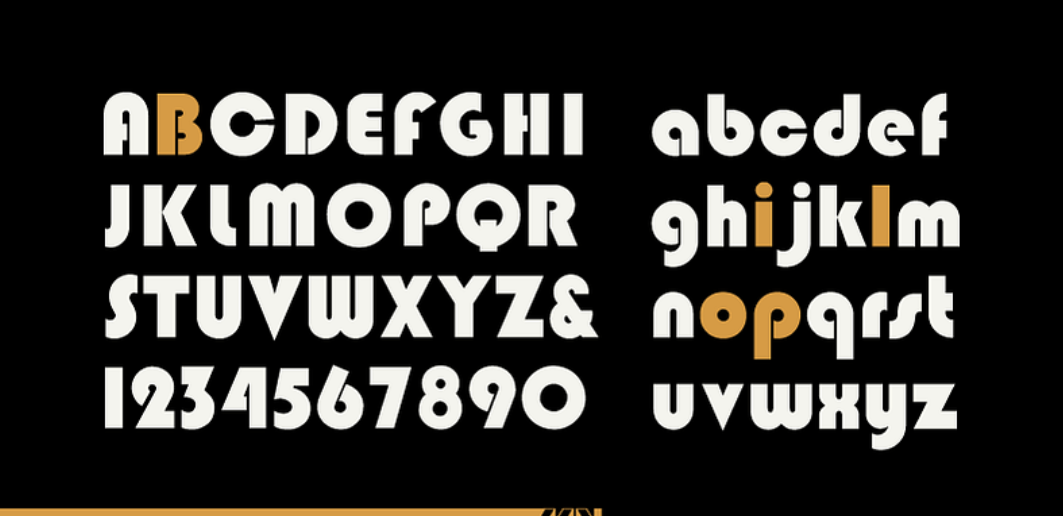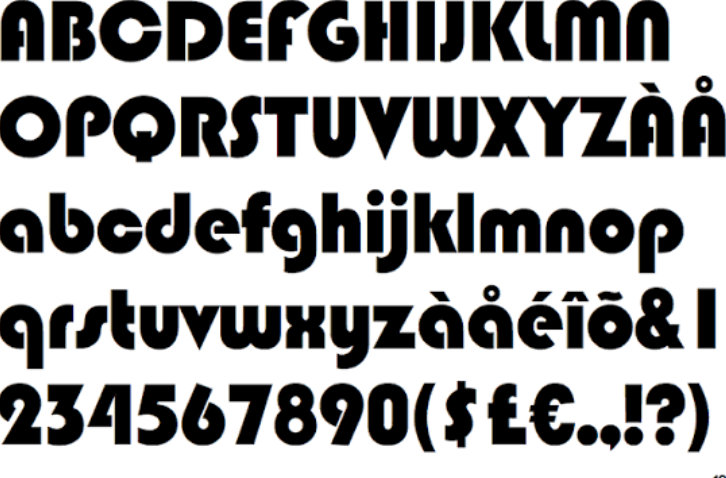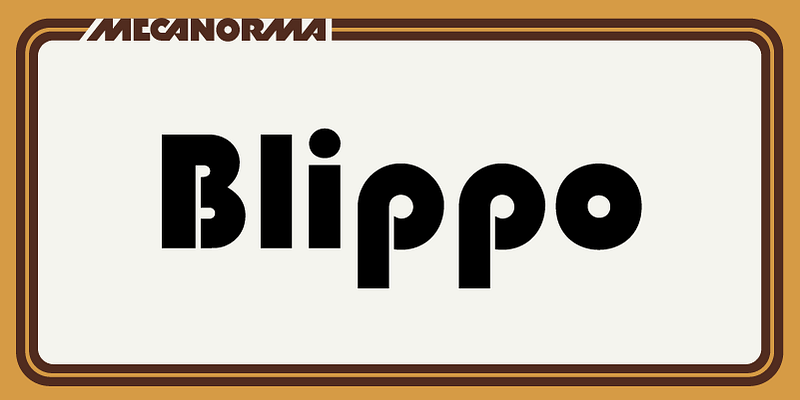
Font Blippo Việt hóa là bộ phông chữ thuộc dòng Display Sans-serif siêu đậm mang phong cách Retro thập niên 1970, nổi bật với cấu trúc hình học mập mạp và các góc bo tròn hoàn toàn. Được sáng tạo ban đầu bởi nhà thiết kế Robert Trogman, Blippo (bao gồm các biến thể nổi tiếng như Blippo MN và Blippo Bold) mang lại diện mạo vô cùng vui tươi, rực rỡ và tràn đầy năng lượng tích cực. Doozypack.vn cung cấp link Font Blippo Free Download chuẩn kỹ thuật, giúp bạn sở hữu phông chữ độc đáo này, hỗ trợ đầy đủ tiếng Việt để tự tin thiết kế bao bì và bộ nhận diện thương hiệu mang hơi hướng hoài cổ.
Đặc điểm thẩm mỹ độc đáo của bộ font Blippo
Blippo không đi theo sự thanh mảnh hay sắc nhọn; nó tạo ra một ngôn ngữ thị giác đầy đặn, vui nhộn và mang đậm tinh thần giải trí của văn hóa Pop-art thế kỷ 20.
Phong cách Retro 1970s mập mạp và tràn đầy năng lượng
Đặc trưng lớn nhất của Font Blippo Việt hóa là độ dày nét chữ (weight) cực lớn kết hợp cùng các góc bo tròn khép kín. Cấu trúc chữ gợi liên tưởng đến những khối bong bóng căng phồng hoặc các ký tự trên bìa đĩa nhạc Disco xưa. Khi đặt Blippo làm tiêu đề trên bao bì, sản phẩm của bạn sẽ ngay lập tức thu hút ánh nhìn nhờ vẻ ngoài nổi bật, hóm hỉnh và cực kỳ thân thiện với người tiêu dùng.
Cấu trúc chữ siêu đậm (Extra Bold) với các góc bo tròn độc đáo
Các ký tự trong Blippo Bold sở hữu tỷ lệ x-height rất lớn, gần như không có khoảng trắng thừa bên trong các chữ cái nhỏ (counter rất nhỏ). Thiết kế này tạo ra một mảng khối đặc biệt vững chãi, giúp tên thương hiệu hoặc các khẩu hiệu ngắn hiển thị dứt khoát, uy lực và không thể bị lu mờ trên kệ hàng.
Ưu điểm nổi bật của bản Font Blippo Việt hóa
Khi ứng dụng các phông chữ siêu đậm vào thị trường trong nước, sự chỉn chu về dấu câu là yếu tố quyết định đến tính chuyên nghiệp của ấn phẩm:
- Khắc phục triệt để lỗi dấu tiếng Việt: Phiên bản Việt hóa đã được đội ngũ thiết kế trau chuốt thủ công từng dấu câu. Các dấu sắc, huyền, hỏi, ngã, nặng được vẽ mập mạp, bo tròn đồng điệu cùng thân chữ gốc, không gây cảm giác chắp vá hay làm biến dạng cấu trúc chữ.
Ứng dụng thực tế của font Blippo trong sản xuất bao bì tại Doozypack.vn
Sự tươi vui và cá tính của Blippo mang lại hiệu ứng thị giác đắt giá trên các dòng sản phẩm bao bì thực tế do Doozypack.vn sản xuất:
- Hộp giấy đựng Bánh kẹo & Snack (Bakery & Confectionery): Tiêu đề thương hiệu in bằng font Blippo kết hợp cùng màu sắc tươi sáng tạo nên vẻ ngoài ngon miệng, ngọt ngào và kích thích sự thèm ăn của khách hàng.
- Tem nhãn dán Trà sữa & Nước giải khát: Cấu trúc chữ béo mập rất thích hợp để in các tem decal tròn dán lên ly nước, giúp sản phẩm trông sinh động và trẻ trung hơn.
- Túi giấy thời trang Streetwear & Quà lưu niệm: Tên cửa hàng in bằng font Blippo trên nền túi giấy trắng cán màng mờ tạo phong cách năng động, cá tính và cực kỳ sành điệu.
03 Lưu ý kỹ thuật khi in ấn với phông chữ siêu đậm Blippo
Việc sản xuất bao bì thực tế sử dụng các phông chữ có độ phủ mực lớn như Blippo đòi hỏi sự am hiểu kỹ thuật chuyên sâu tại xưởng in Doozypack.vn:
- Kiểm soát hiện tượng tràn mực (Dot Gain) tại khe chữ nhỏ: Các khoảng hở bên trong chữ cái của Blippo (như chữ ‘e’, ‘a’) cực kỳ hẹp. Khi in trên giấy có độ thấm mực cao như giấy Kraft, mực có thể bị lan làm bít kín các lỗ hở này. Bạn nên giữ size chữ tiêu đề tối thiểu từ 10pt trở lên để bảo đảm độ sắc nét.
- Lựa chọn hệ màu rực rỡ: Phong cách Blippo đẹp nhất khi phối cùng các tông màu tươi sáng hoặc màu tương phản mạnh (chữ vàng viền đen, chữ trắng trên nền cam). Một đường viền (Stroke) mỏng quanh chữ cũng giúp tiêu đề trông “nổi” và sắc nét hơn trên vỏ hộp.